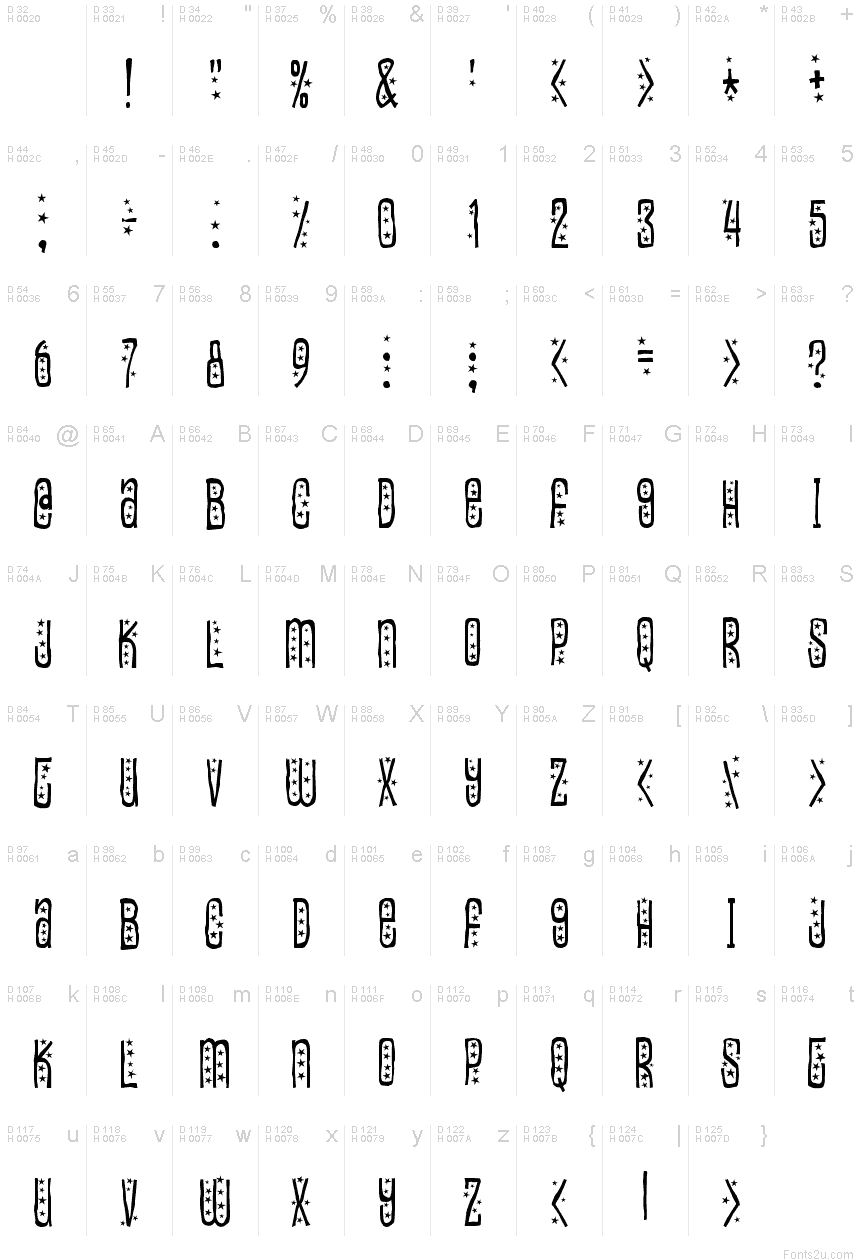
Easily amused autorstwa Jakoba Fischera to darmowy, dekoracyjny krój pisma, który wygląda, jakby był oświetlony od wewnątrz. Wysokie, zaokrąglone litery wypełniają wyraziste kształty gwiazd, dzięki czemu każde słowo przypomina mały, podświetlany szyld. Czerń liter i ciasne krzywe nadają mu klimat retro wesołego miasteczka – czcionka jest wystarczająco wyrazista, by przykuć uwagę, a jednocześnie pozostaje czytelna w krótkich tekstach.
Easily amused sprawia, że każdy nagłówek staje się świętem. Świetnie sprawdzi się na zaproszeniach urodzinowych, plakatach dla dzieci, ulotkach imprezowych, opakowaniach zabawek, zabawnych logotypach czy grafikach do mediów społecznościowych. Ten darmowy font najlepiej prezentuje się w dużych rozmiarach, gdzie gwiazdkowe detale mogą w pełni błyszczeć. Aby zachować czytelność i równowagę w całym projekcie, najlepiej łączyć go z prostym krojem bezszeryfowym w tekstach pomocniczych.